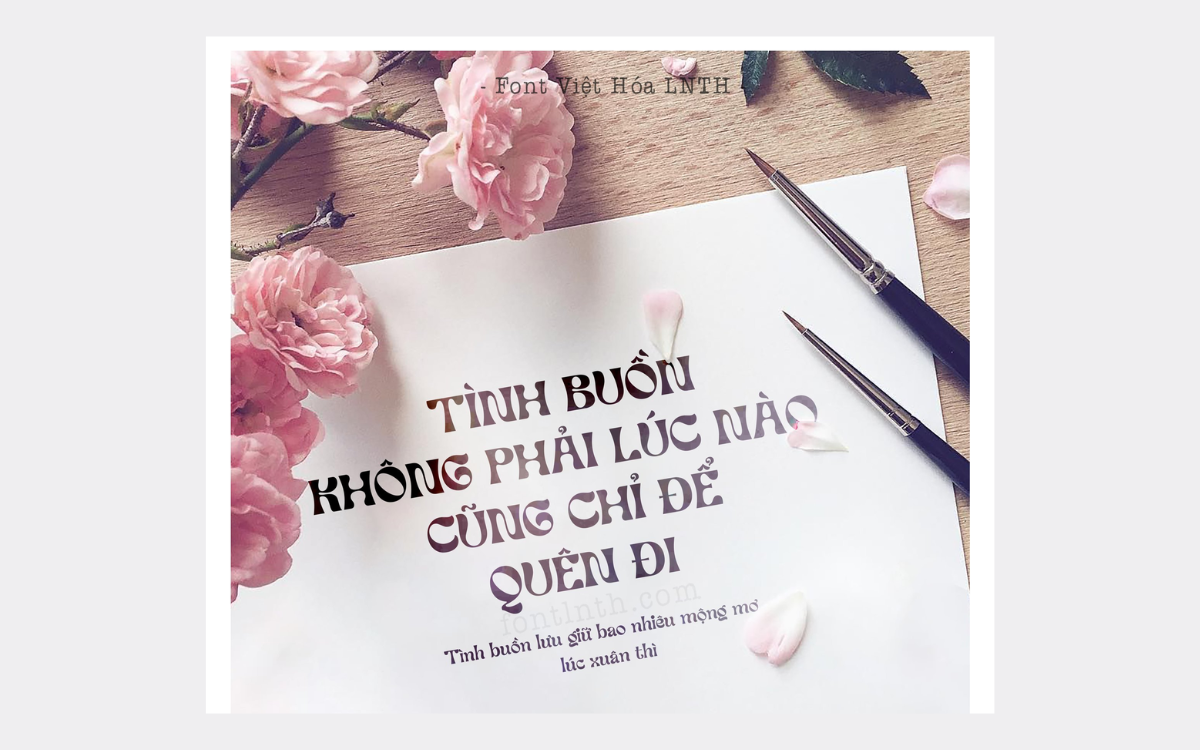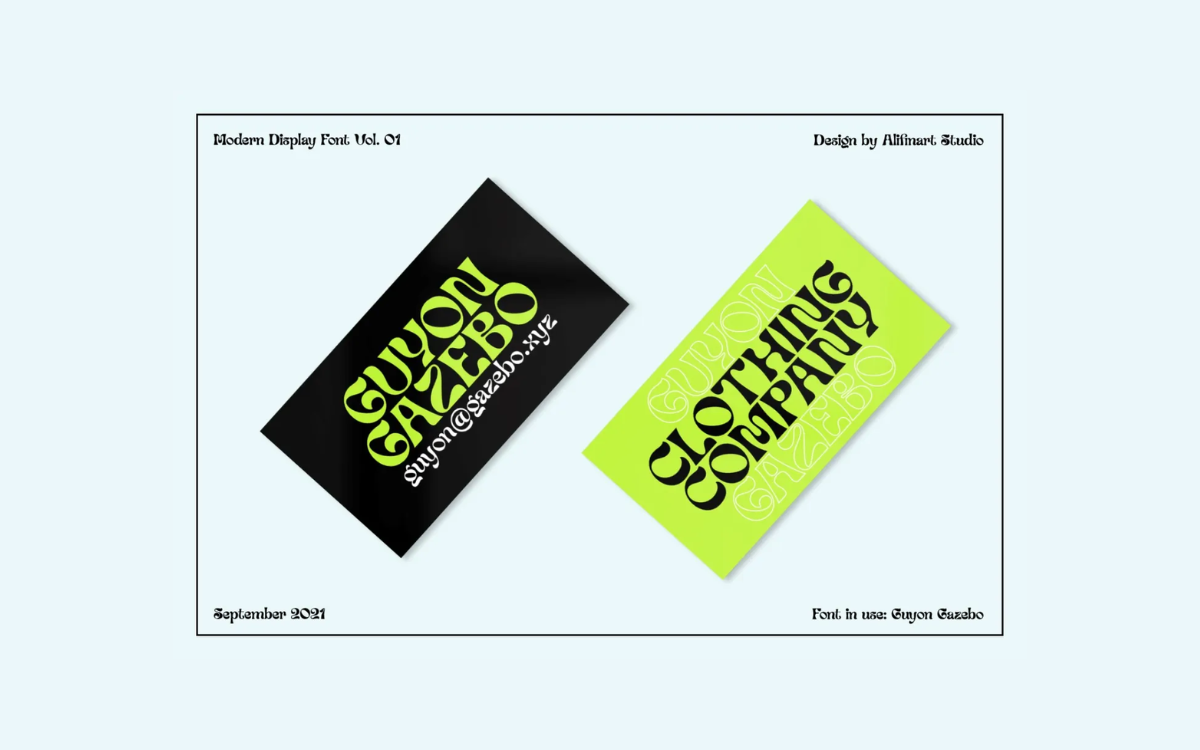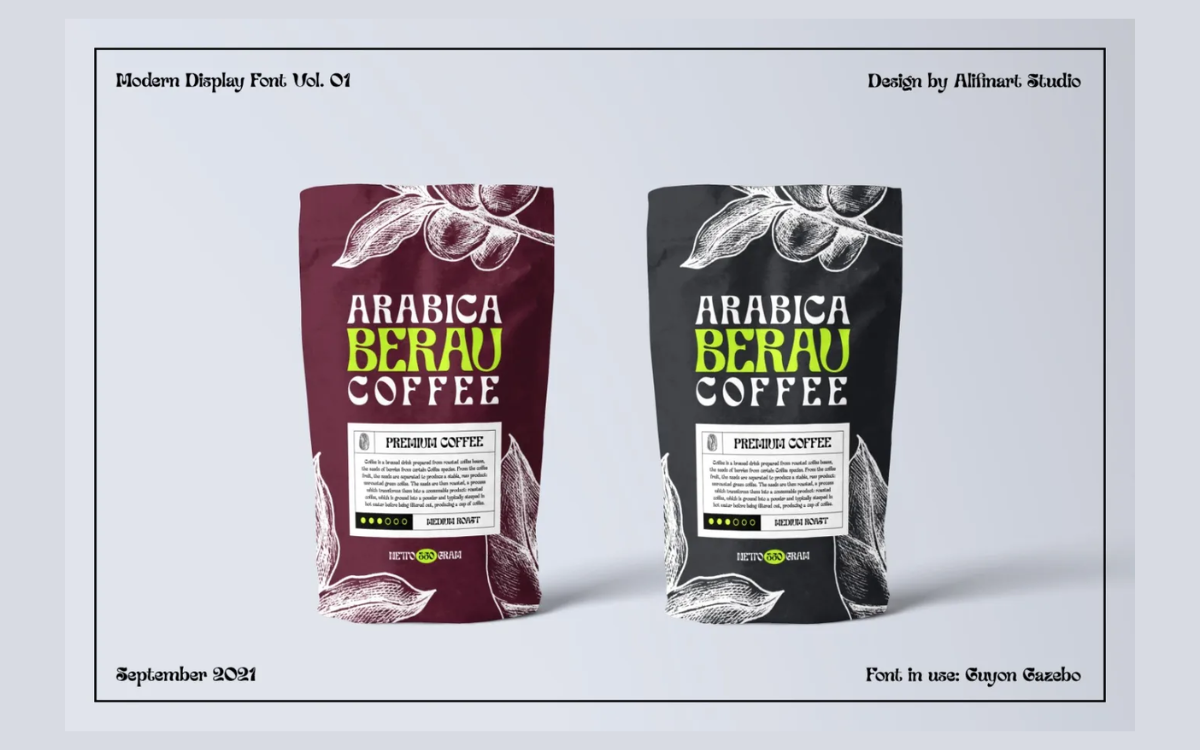
Font LNTH Guyon Gazebo
Kiểu chữ: Serif
Độ dày: Thin, Light, Regular, Medium, Bold, Black
Font LNTH Guyon Gazebo là sự lựa chọn tuyệt vời cho những ai muốn mang đến một phong cách độc đáo và đầy sáng tạo cho thiết kế của mình. Với nét chữ tinh tế, đậm chất nghệ thuật, Font LNTH Guyon Gazebo thuộc bộ font chữ không chân. Điều này tạo nên sự pha trộn hoàn hảo giữa cổ điển và hiện đại, giúp các dự án của bạn trở nên nổi bật và thu hút. Font LNTH Guyon Gazebo không chỉ mang lại cảm giác sang trọng và thanh lịch, mà còn thể hiện sự sáng tạo đầy cá tính. Đây là font chữ lý tưởng cho các ấn phẩm cần sự ấn tượng và độc đáo, từ thiết kế logo, tiêu đề cho đến các sản phẩm truyền thông đa dạng.